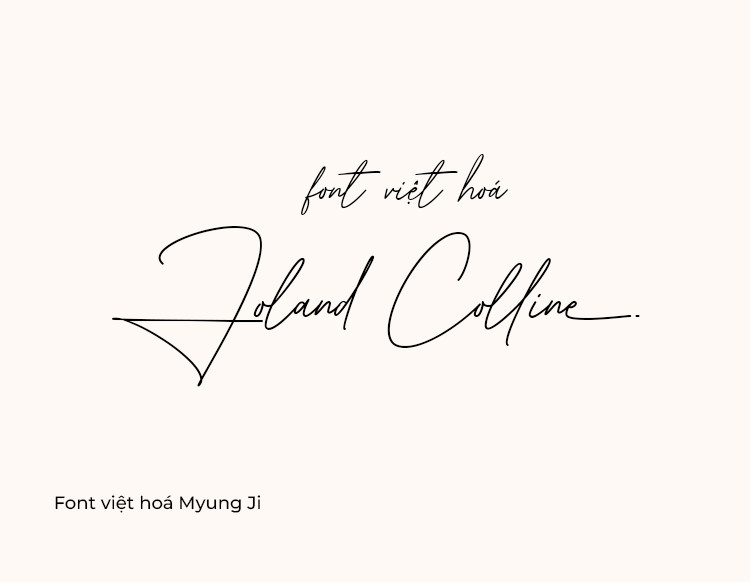
Giới thiệu về Font việt hoá MJ Joland Colline
Trong thế giới thiết kế đồ họa, việc lựa chọn một Font Chữ phù hợp đóng vai trò quyết định đến linh hồn của tác phẩm. Font việt hoá MJ Joland Colline là một bộ phông chữ thuộc phong cách Script đầy tinh tế, mang lại cảm giác nhẹ nhàng, bay bổng và vô cùng sang trọng. Với các đường nét thanh mảnh được trau chuốt kỹ lưỡng, bộ font này cực kỳ phù hợp cho các dự án thiết kế mang tính nghệ thuật cao như thiệp cưới, bìa sách, hay các ấn phẩm giáo dục đòi hỏi sự thẩm mỹ và chỉn chu.
Đặc điểm nổi bật của MJ Joland Colline
MJ Joland Colline sở hữu các đường lượn sóng tự nhiên, tạo nên một nhịp điệu thị giác uyển chuyển. Khi được việt hóa, bộ font này đã được tối ưu hóa hoàn toàn các dấu câu tiếng Việt, đảm bảo không xảy ra lỗi hiển thị hay mất nét khi gõ văn bản. Điều này giúp các bạn học sinh và giáo viên dễ dàng ứng dụng vào việc làm slide bài giảng hoặc trang trí báo tường một cách sinh động nhất.
Cách ứng dụng Font việt hoá MJ Joland Colline hiệu quả
Để phát huy tối đa vẻ đẹp của Font việt hoá MJ Joland Colline, người dùng nên kết hợp nó với các font chữ không chân (Sans-serif) đơn giản để tạo sự cân bằng. Các bạn có thể sử dụng font này cho các tiêu đề chính nhằm thu hút ánh nhìn, sau đó dùng các phông chữ hiện đại khác cho phần nội dung chi tiết. Sự tương phản này sẽ làm nổi bật nét đẹp cổ điển nhưng không kém phần hiện đại của MJ Joland Colline trong mọi không gian thiết kế số.